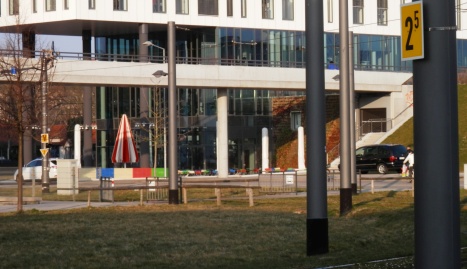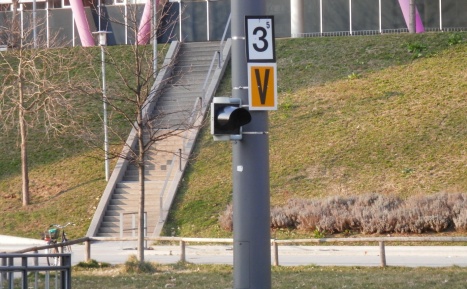
Schraubensortiment etikettieren (bei wenig Platz: 17 mm × 4,6 mm)
Nun, den engen Abstand habe ich wegen der Vorgabe "wenig Platz" bewusst gemacht, ein scxhmales Leerzeichen hat der Spezialfont (noch) nicht, aber man könnte, da man mit diesem Spezialfont ja eigentlich nicht richtig schreiben können muss, durchaus durch deutliche Verschmälerung des normalen Leerzeichens machen.In so einem Spezialfont ist praktisch alles erlaubt.
Wie Gewindesorten am besten als Symbol darstellen sollte, also Maschinengewinde, Holzschraube, Schnellbauschraube, Spanplattenschraube? Da fällt mir im Moment nichts gutes ein, wer weiß...
Wie funktioniert das mit den Logos und der Nachkomma-Automatik?
Nun, in beiden Fällen gleich: Sowohl für die Symbole als auch für diese Nachkommastelle (übrigens nur eine! Mehr wird ja praktisch nie gebraucht) habe ich Codesw hinterlegt, für die dann die jeweilige Glyphe eine "Ligatur" ist, in etwa so, wie in einer normalen Schrift aus f + i eine fi-Ligatur werden kann, ist der Innensechskantkopf eine Ligatur aus I + N oder das kleine ,6 ist eine Ligatur (also nur ein Zeichen) aus "comma" und "six".
Das tolle daran, man kannpraktisch beliebig viele Zeichen so durch ein einziges ersetzen, so bau ich auch gern mein Logo ein, dass sich dann als Easteregg hinter einem ganzen Wort verbirgt. Wer hier meinen Nick kennt, findet in der neuen Version das dann mein Logo. Mit OpenType kann man einfach phantastische Dinge im Font unterbringen...
Danke. Ich hatte gehofft, man könne über spezifische Konfiguration der Schrift im OS etwas erreichen.
Schade, dann sind die Früchte des schönen Fonts Schraubenkiste für mich weder in Libreoffice noch in meinem Etikettendrucker erreichbar.
Nun, das ist leider die Krux. Libre- und OpenOffice haben sich, da dieses kostenlose Paket sich ja auch an Nutzer wendet, die von Microsoft komplett links liegen gelassen werden, nämlich Menschen mit Minderheitensprachen für ein anderers Smartfont-System entschieden: SIL Graphite. Der Ansatz ist hier ein anderer, nicht tolle Design-Spielereien, sondern die Möglichkeit, die Zeichen von Minderheitensprachen, bei der oft ein ganzes Rudel an Zeichen gestapelt werden müssen, überhaupt darstellen zu können, und da steckt eben die Strärke von Graphite.
Aber das isat nicht das Aus für "Schraubenkiste" - wenn auch das einen Verlust an Bequemlichkeit bedeutet - oder besser - bedeuten kann, es gibt nämlich mehrere Möglichkeiten:
Die Bequemste: Es gibt ein weiteres kostenloses Textprogramm, das zumindest die OpenType-Ligaturen gut unterstützt: Abiword.
Für die nächsten Lösungen: Die Symbole und Nachkomma-Ziffern besitzen auch einen Unicode-Platz im so genannten Private Use Area. Die Codes dazu stehen etwas weiter oben in einem früheren Beitrag von mir.
Jetzt gibt es ein Programm, das eigentlich für die Nutzung von Frakturschrift ohne Opentype entwickelt wurde: Ligafaktur heißt es ( http://www.ligafaktur.de/ ) - dieses Programm kann aber auch sehr gut für eine deutlich einfachere Eingabe von Unicodes genutzt werden.
Die Codes der Nachkommastelle ist übrigens E02x mit x = der Ziffer.
Weniger Komfortabel, aber durchaus gangbar: Man Kopiert sich die Texte aus der Windows-Zeichentabelle zusammen ( charmap.exer in alle Programme -> Zubehör
Das ist die korrigierte Version mit verschmälertem Leerzeichen
Mir ist ein erster Ausdruck auf dem Etikettendrucker gelungen.
Ich habe in der Libreoffice-Calc-Datei, aus welcher der Etikettendrucker seine Inhalte bezieht, per Windows-Zeichentabelle die Symbole eingefügt.
Bei einem Schriftgrad von 16 nimmt der Beispielinhalt eine Breite von 15,2 mm ein.
Nicht gefunden habe ich in der Zeichentabelle die Ligaturen ",5" etc.
Erwartungsgemäß ist bei der geringen Auflösung des Druckers (Brother 1230PC, Band TZe-211) der Druck fransig.
Aber auch bei den feinen Strukturen des Torx-Kopfes ist dieser hinreichend gut erkennbar.
Was mir noch auffällt:
Das Komma ist sehr kurz.
Der vertikale Strich der "4" verschmilzt fast mit dem Strich links oben.
In der Druckvorschau
ist der Abstand zwischen "5" und dem Torx-Symbol größer. Im Ausdruck verschmilzt er leider fast mit der "5".
Die vertikale Lage ist anders als bei anderen Schriften. Sie ist höher. Unterkante Komma und Oberkante Versalien stehen vertikal zentriert innerhalb der Zeilenhöhe. Mich irritiert das ein wenig. Aber das muss ich noch sacken lassen.
Zu den Gewinden:
Ich kam eigentlich nur drauf, weil Du ein "M" (vermutlich) zur Kennzeichnung eines metrischen Gewindes verwendet hast. Beim Spax-Gewinde jedoch keine gesonderte Kennzeichnung.
Für meine konkrete Situation mit der Aufsicht ist eigentlich jedwede Kennzeichnung des Gewindes "zu viel".
Man erkennt es leicht und der Platz ist für ein weiteres Symbol einfach zu knapp.
Anders sähe es in Situationen aus, wo man die Objekte nicht direkt einsehen kann (Front von Kästen).
• Keinen Schaft oder nur einen Stummel
Hier noch einige Abbildungen von Kopfprofilen ohne Schaft bei einem Schraubenhändler:
Abschnitt 2.2
Bullets
Nun, hier bietet der Standardsatz von Unicodezeichen ja schon "periodcentered" (U+00B7) (kleines Zeichen) und "bullet"  (U+2022) (größeres Zeichen).
Ich fände einen dritten "Punkt" in einem Durchmesser toll, der zwischen diesen beiden liegt.
Mir ist jedenfalls oft "periodcentered" zu klein und "bullet" zu groß.